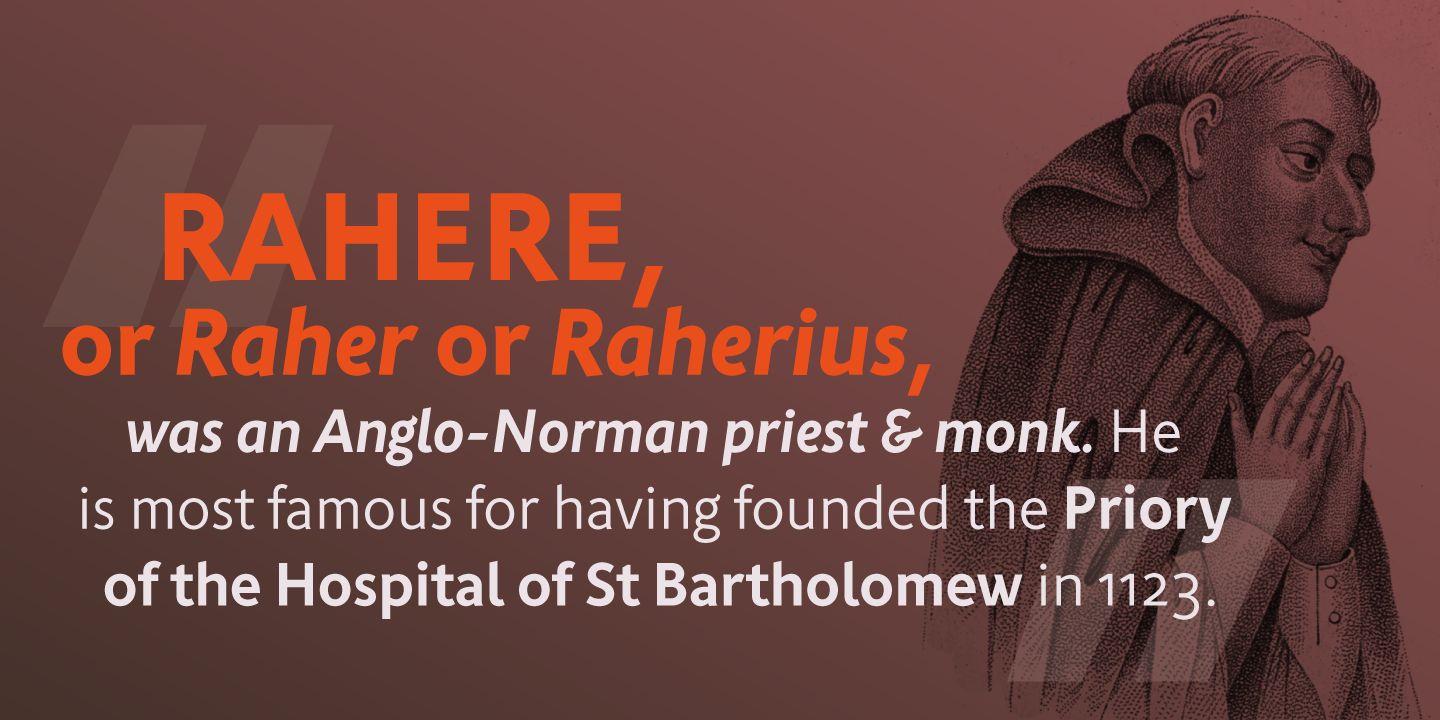
Rahere Sans Font Family
Description de Rahere Sans Font Family
Rahere est un sans humaniste avec des caractéristiques subtiles qui donnent à la police une apparence distinctive et chaleureuse sans distraire le lecteur. Lisible en grand et petit format, Rahere est une famille polyvalente adaptée à un large éventail d’applications telles que les rapports annuels, la publicité, les brochures, les catalogues, la signalisation informative, les textes sur écran et les identités visuelles. Pour les projets qui doivent transmettre un sentiment d’autorité ou de crédibilité, c’est le sans empattement idéal à utiliser.
La famille se compose de six graisses allant du léger au gras extra avec l’italique correspondant et le jeu de caractères couvre la plupart des principales langues européennes. Chaque poids contient des chiffres alignés et non alignés dans un espacement proportionnel et tabulaire. Les chiffres tabulaires partagent la même largeur dans tous les poids et styles – un incontournable pour les tableaux financiers des rapports annuels. Fougueuse et vivante, la minuscule italique est plus cursive et calligraphique que la romaine, bien qu’elle s’harmonise parfaitement, affichant suffisamment de caractère pour créer de l’emphase sans paraître déplacée. Lorsqu’il est utilisé seul, pour des citations ou de la poésie, l’italique dégage un charme qui attire l’attention sur le texte.
La police de caractères porte le nom de Rahere, un prêtre anglo-normand du XIIe siècle, qui a fondé le St Bartholomew’s Hospital de Londres en 1123. Je serai toujours redevable à Barts (comme on l’appelle maintenant communément) car en 2007, j’ai été soigné avec succès pour une rechute. cancer des testicules. En 1992, j’ai conçu mon premier sans empattement, Charlotte Sans, et bien qu’il ait été relativement réussi, je n’ai jamais été vraiment satisfait du résultat final : pas assez de graisses et d’italiques, un petit jeu de caractères, un manque de caractères accentués et mon design. les compétences en étaient encore à leurs balbutiements. Bien que Rahere partage de nombreux éléments communs avec Charlotte Sans, il s’agit bien plus qu’une simple refonte ; cela représente plus de 20 ans de connaissances et d’expérience accumulées en tant que designer.